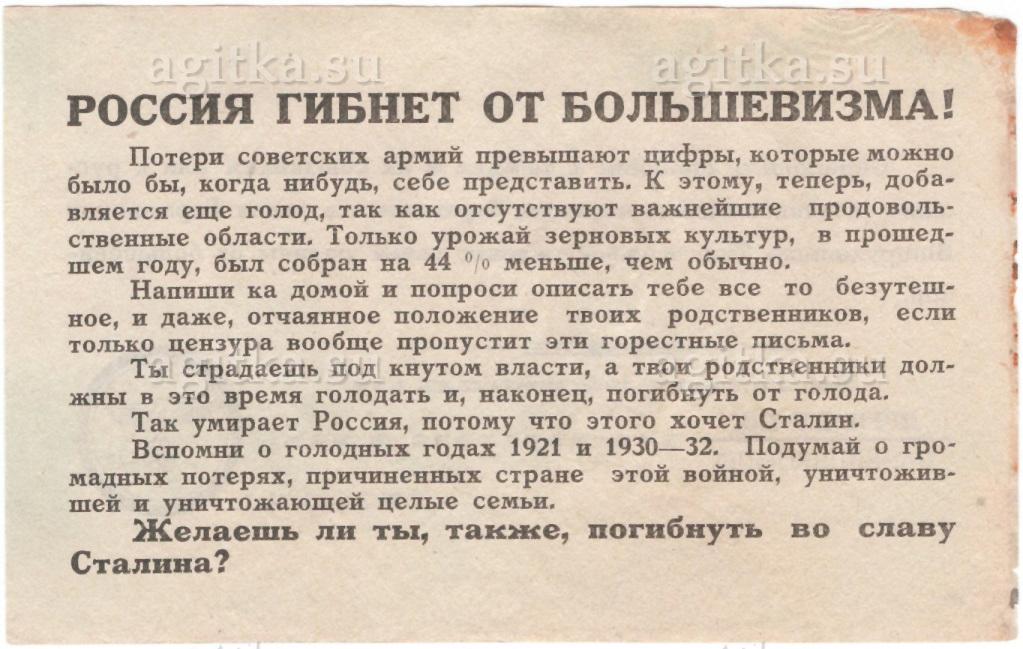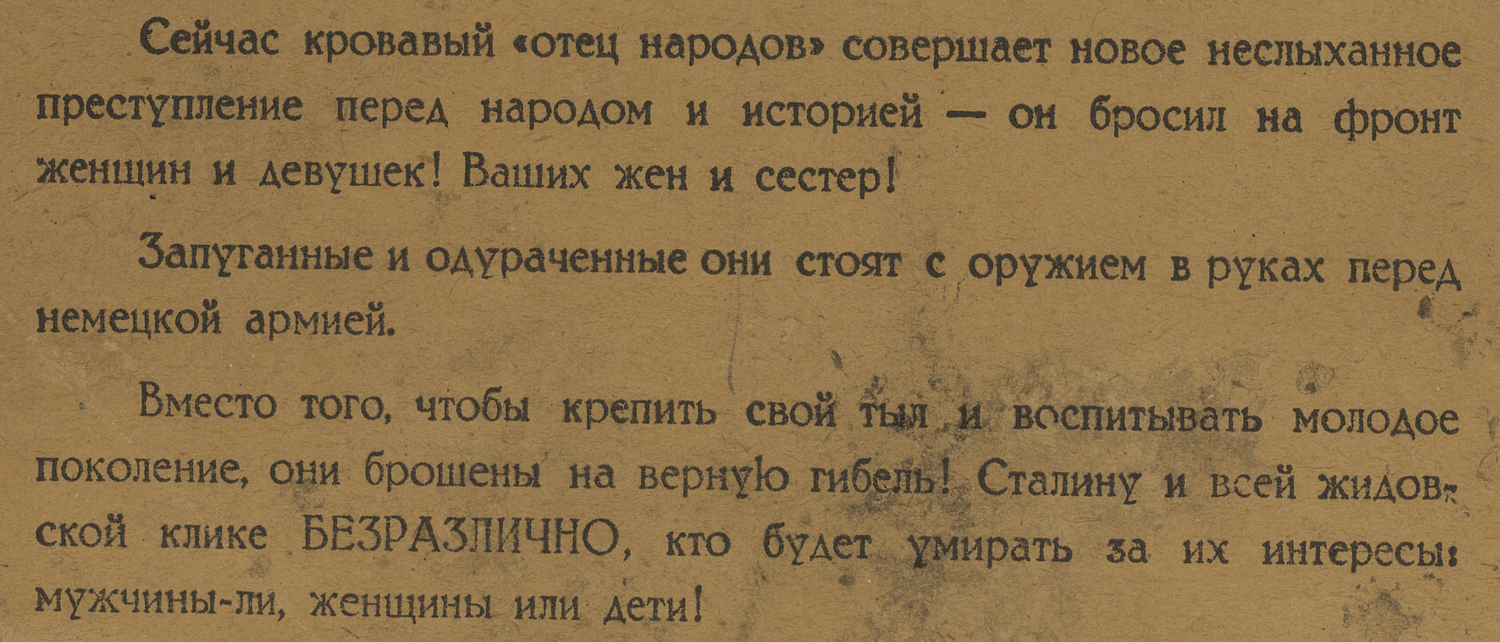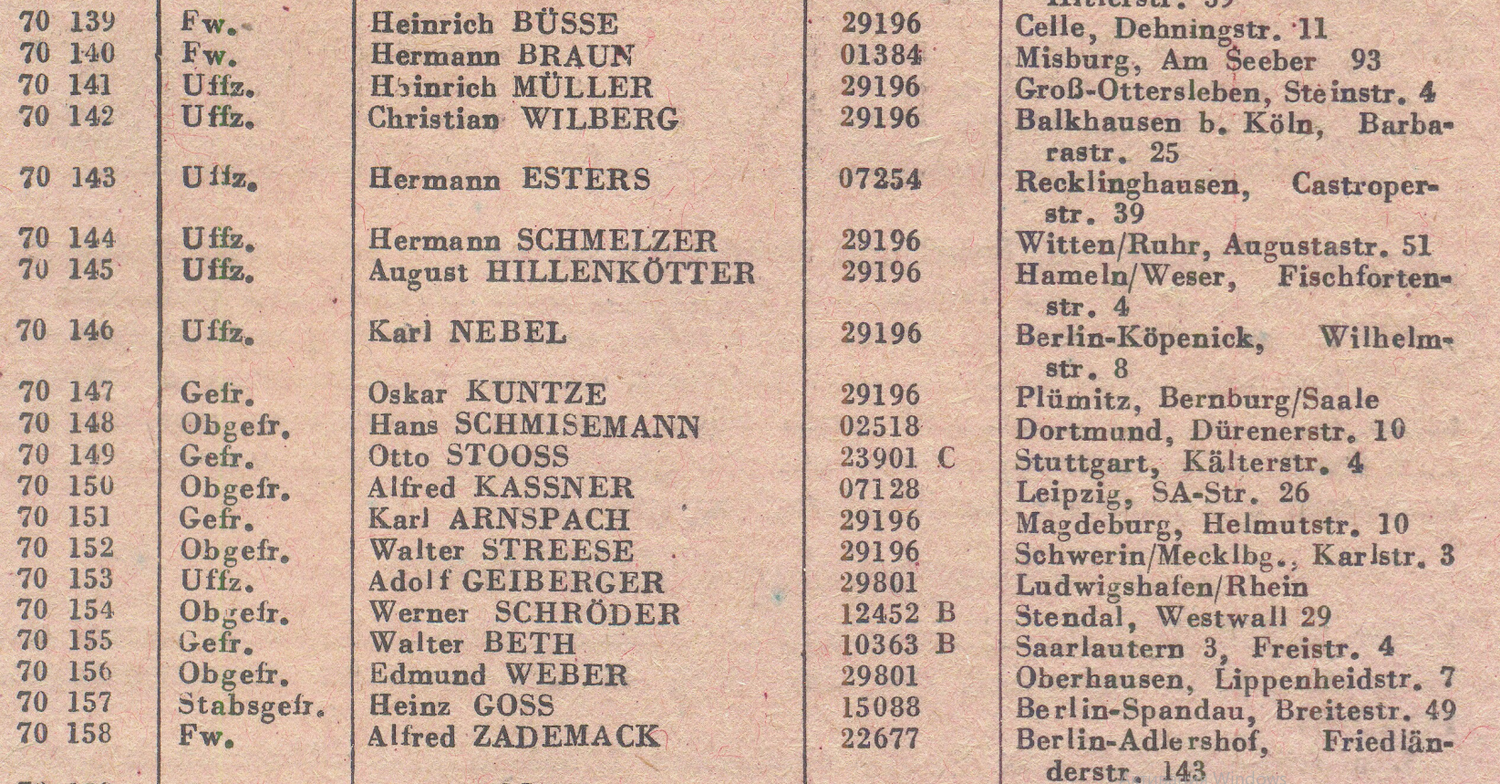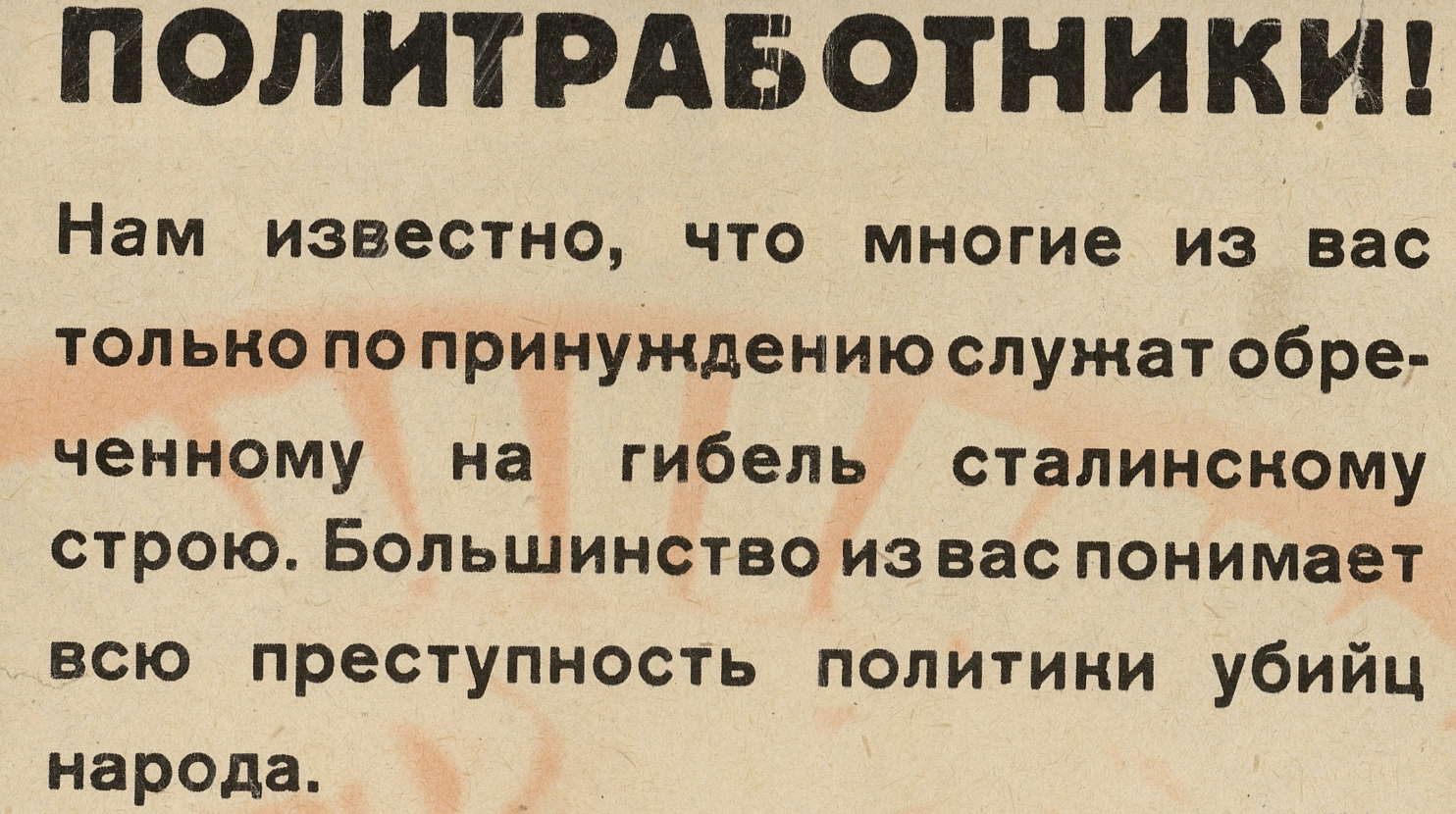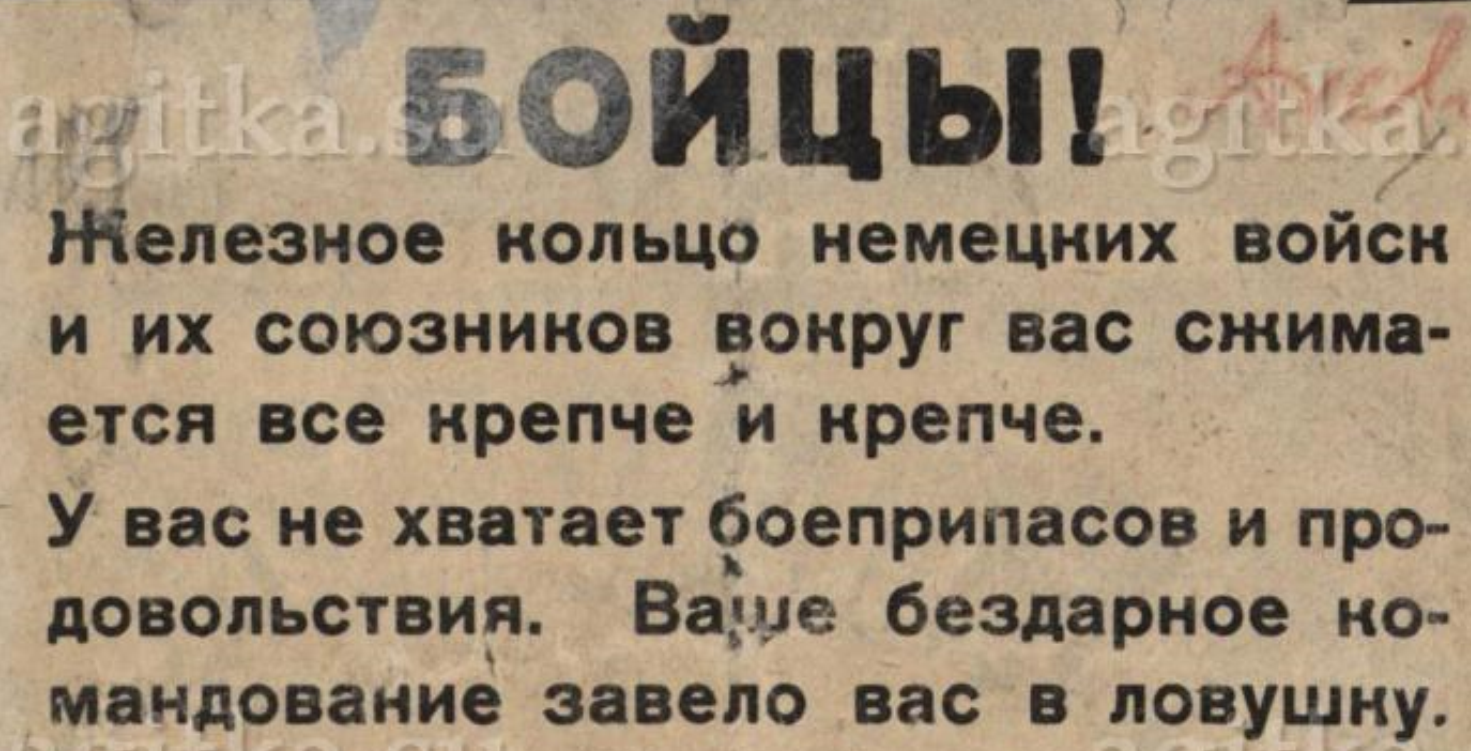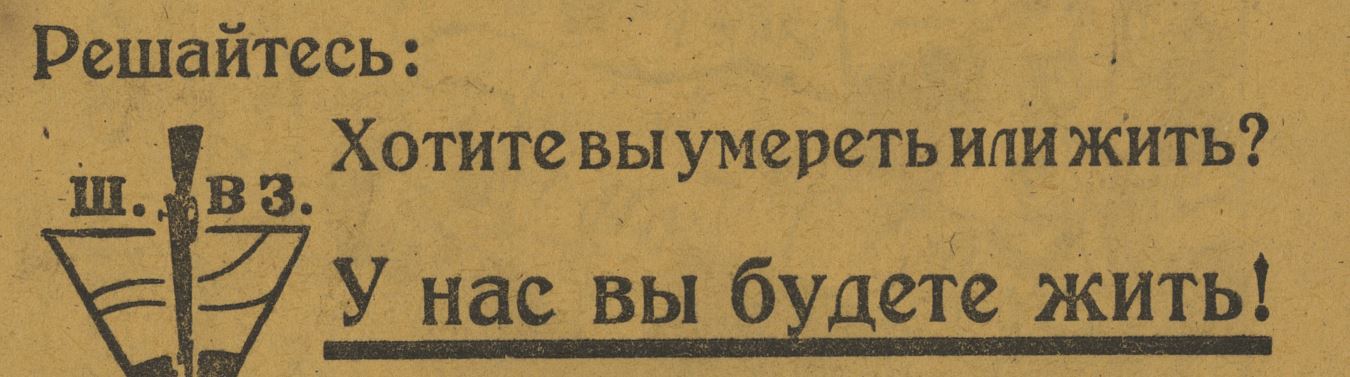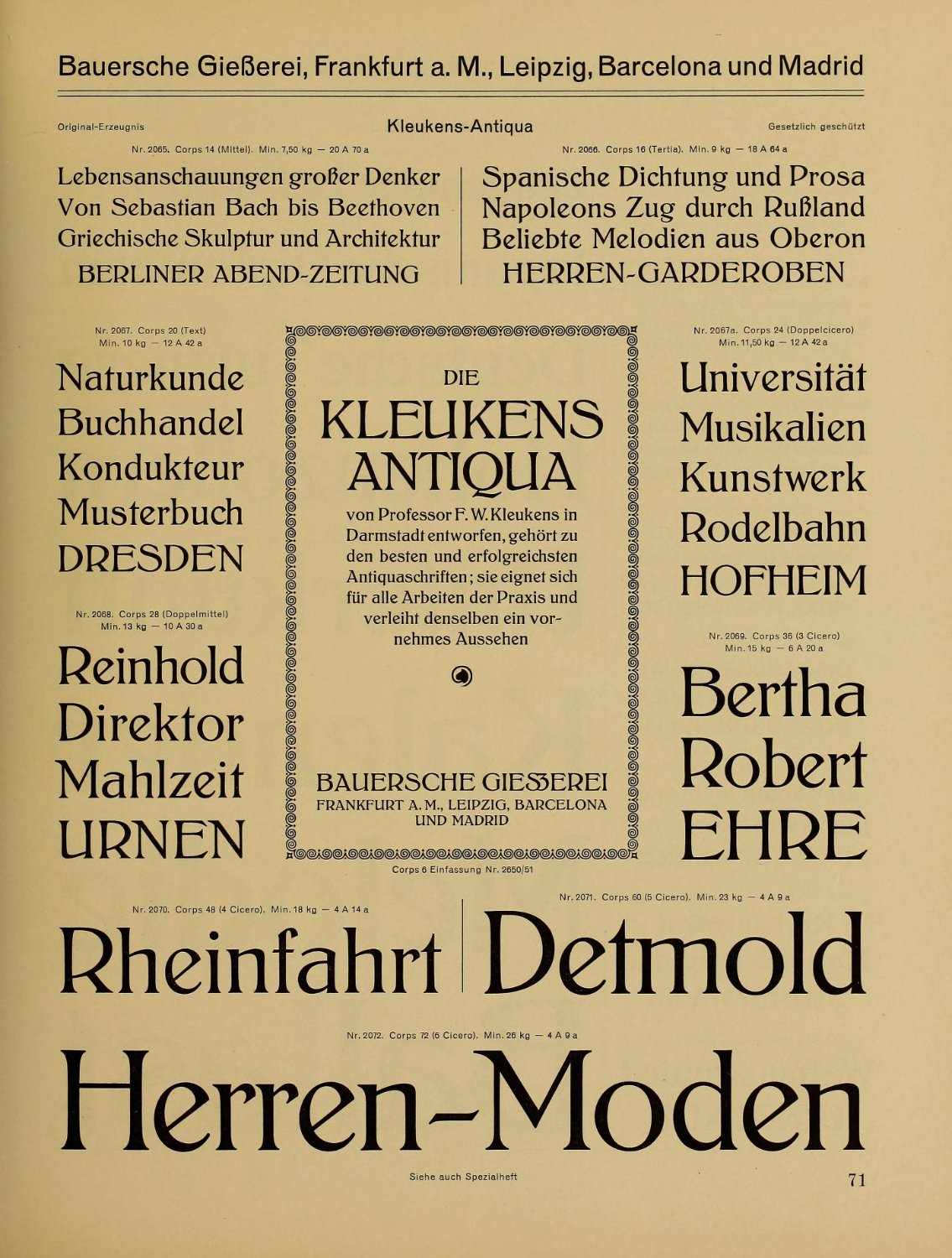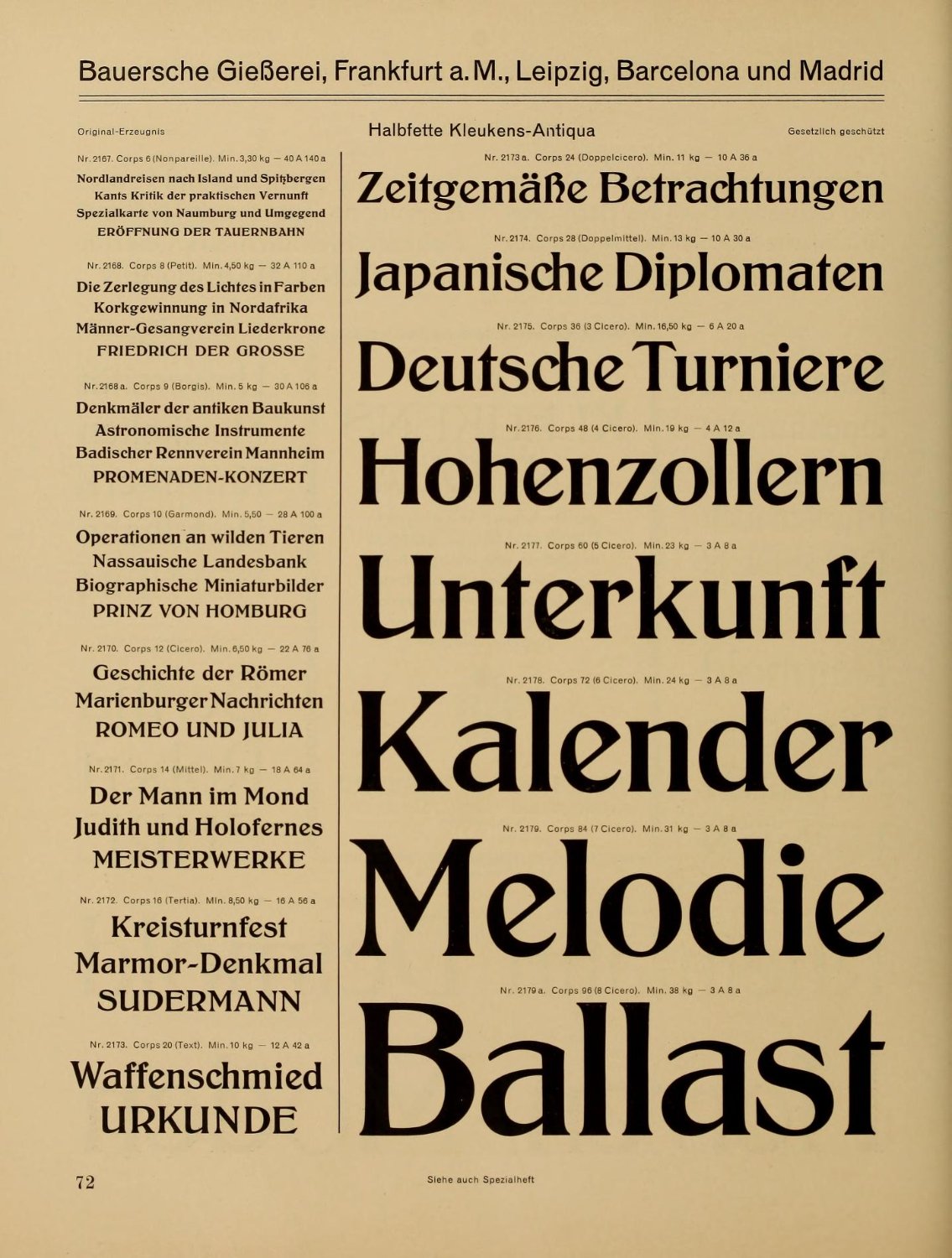
Шрифты в немецких и советских листовках 1941-1945
немцы вряд ли выкупали наш набор перед войной
Ну полностью исключить этого нельзя, перед войной это было возможно. Во время войны у немцев уже были трофейные.
немцев периодически "бросало" в части стилей и шрифтов
Может просто шире выбор был и не так унифицировано.
Довольно разнообразные шрифты (и все сразу) применяло Политуправление Сталинградского фронта.
Основной набор, как я понимаю - Латинский гарнитура 27 (Госполиграфтрест 1927 г.).
Гротеск - Полужирный книжный гротеск (Госполиграфтрест 1927 г.).
По русскому тексту "пропуска" не пойму - возможно, один из вариантов Обыкновенной...
Ну полностью исключить этого нельзя, перед войной это было возможно. Во время войны у немцев уже были трофейные.
В целом да, исключать нельзя, я просто исхожу из мысли, что советские шрифты в основном являются подражаниями шрифтам Лемана и Бертольда, кириллические варианты которых у немцев были. Но могли и купить, так сказать, для аутентичности.
Трофейные у них пошли уже к осени 1941 г., когда они захватили ряд крупных городов, откуда не успевали вывезти типографское оборудование и материалы: Минск, Ригу, Таллин, Вильнюс, Псков...
Но у немцев бывали (в основном на уровне каких-то местных выпусков) совсем дикие по шрифтам вещи, попробую найти))
Может просто шире выбор был и не так унифицировано.
Да, у них же не стояло задач оптимизации, стандартизации, как у нас с ОСТ-1337. Все же капитализм, конкуренция крупных игроков)
пока армии "Норвегия" не подвезли типографию
Когда им (680-й роте пропаганды в Рованиеми) типографию подвезли, они стали издавать листовки такого вида (снова упомяну, что публикую чисто из соображений изучения истории, нацизм осуждаю).
Очень интересный шрифт, обратил внимание на "косой" восклицательный знак. Но гарнитуру не пойму...
Решил немного поискать шрифт, которым берлинский отдел пропаганды вермахта набирал листовки с конца апреля 1942 г. по начало января 1943 г. До этого основной рабочей гарнитурой была Renata, но все комплексно изменилось после ряда апрельских директив.
Для примера берeм листовку конца апреля - начала мая 1942 г. и пытаюсь найти довольно приметный заголовочный шрифт. Поиски на pinterest и затем на archive.org привели меня к шрифту Kleukens-Antiqua словолитни Bauersche Giesserei.
Восклицательный знак, буквы с, а, р - идентичны, но начертание у, к - отличается. Может ли быть такое вызвано отличием именно кириллической версии, или все же (что мне кажется вероятнее), я ошибся в определении гарнитуры?
В первых ваших примерах "у" было набито как игрек Y. Так что да, подменяли на то что нашли.
но начертание у, к - отличается
Строчные буквы "y" и "у" обычно одинаковые. В образцах словолитни нет "y" или я не увидел.
Рисунок "Кк" в кириллице обычно отличается, нет выносного элемента у строчной, изогнутые ветви, капли на концах вместо засечек, другое соединение и т.п.
Строчные буквы "y" и "у" обычно одинаковые. В образцах словолитни нет "y" или я не увидел.
Рисунок "Кк" в кириллице обычно отличается, нет выносного элемента у строчной, изогнутые ветви, капли на концах вместо засечек, другое соединение и т.п.
Вот нашел начертание строчной "y" в том же каталоге по ссылке. Это было ппц сложно - немцы практически не используют ее, нашелся на английском стишок)) Она, конечно, отличается. В кириллической на хвосте капля, в латинской - засечка.
Первый пост, вторая листовка
Остальные примеры, как мне кажется, похожи на Акциденц-Гротеск словолитни Бертольда: